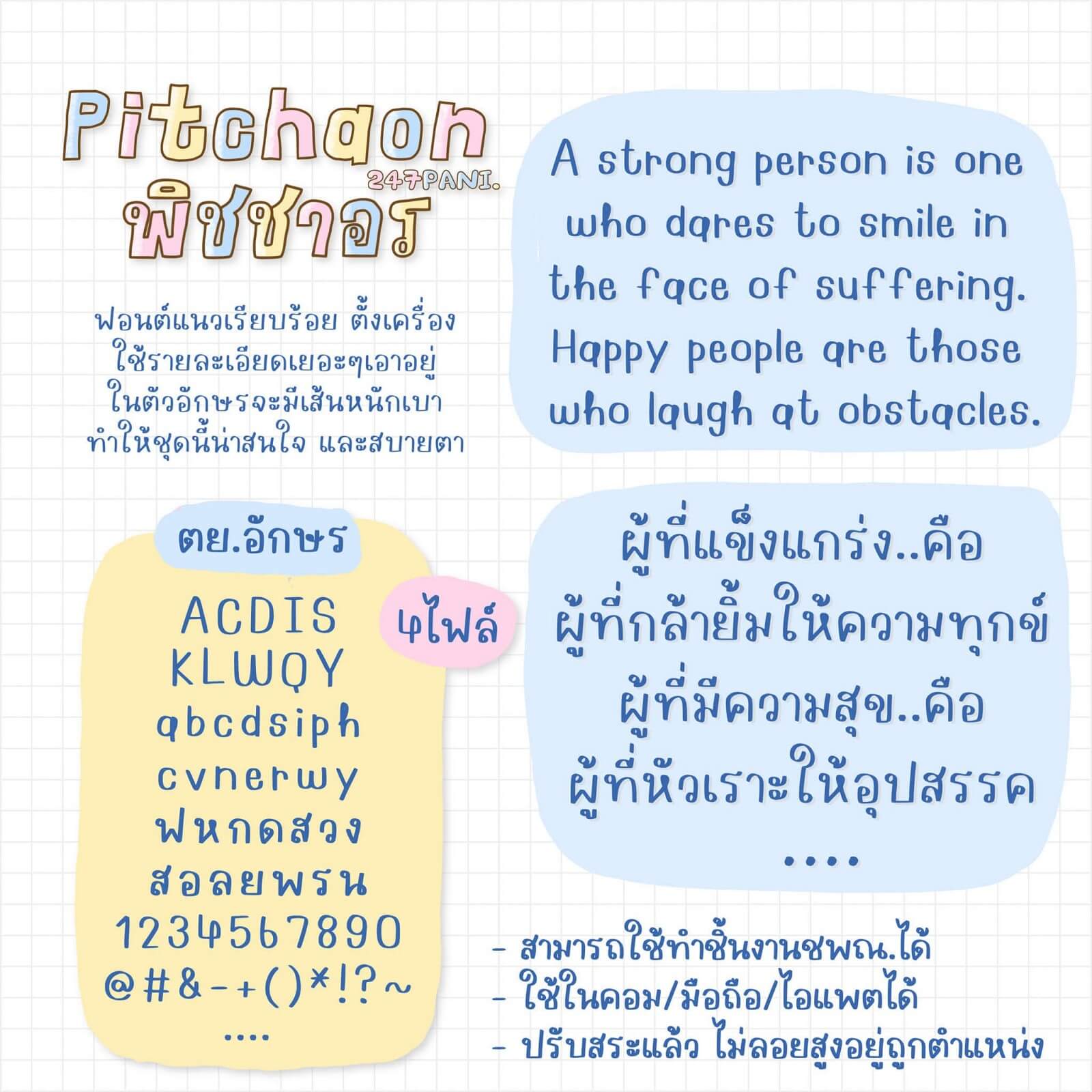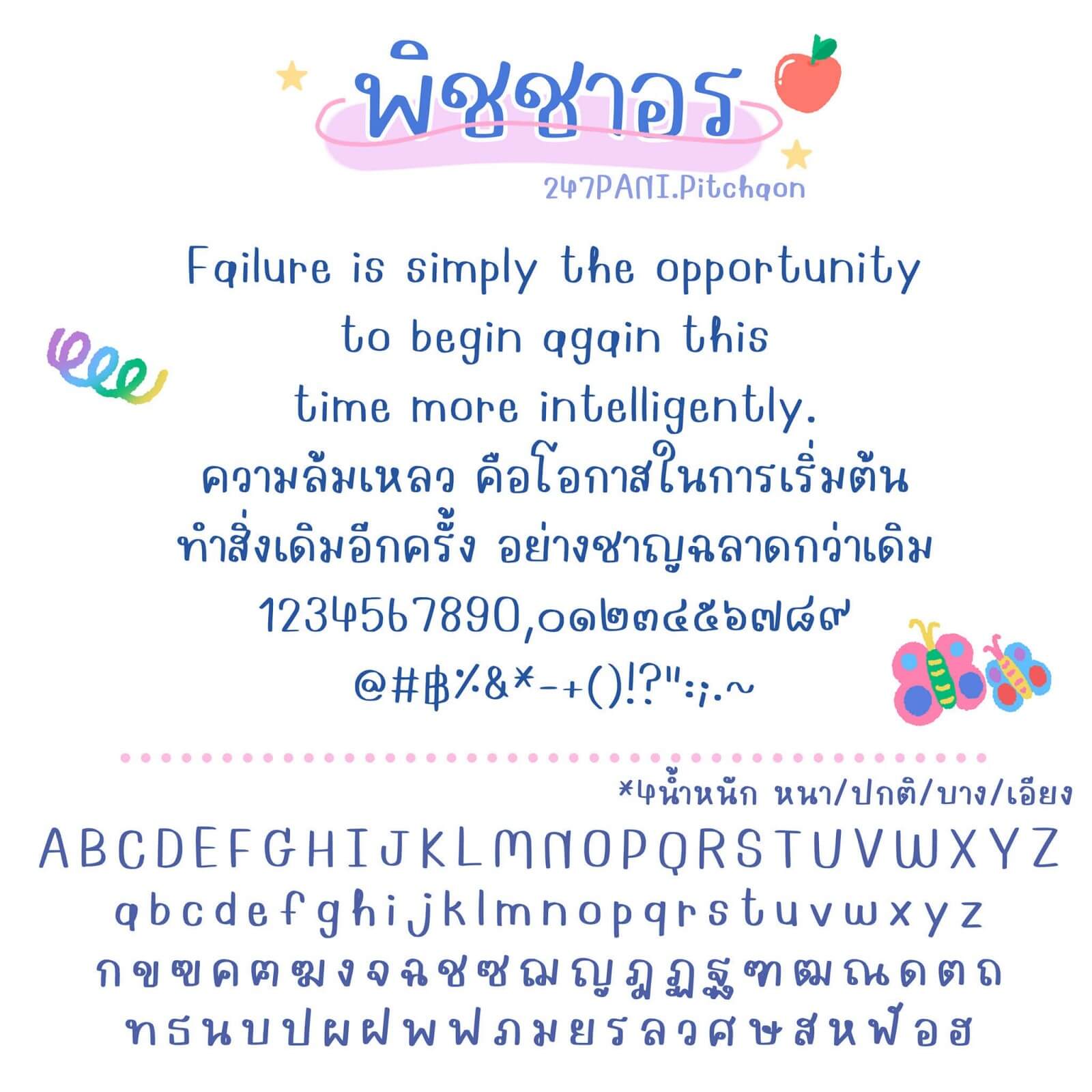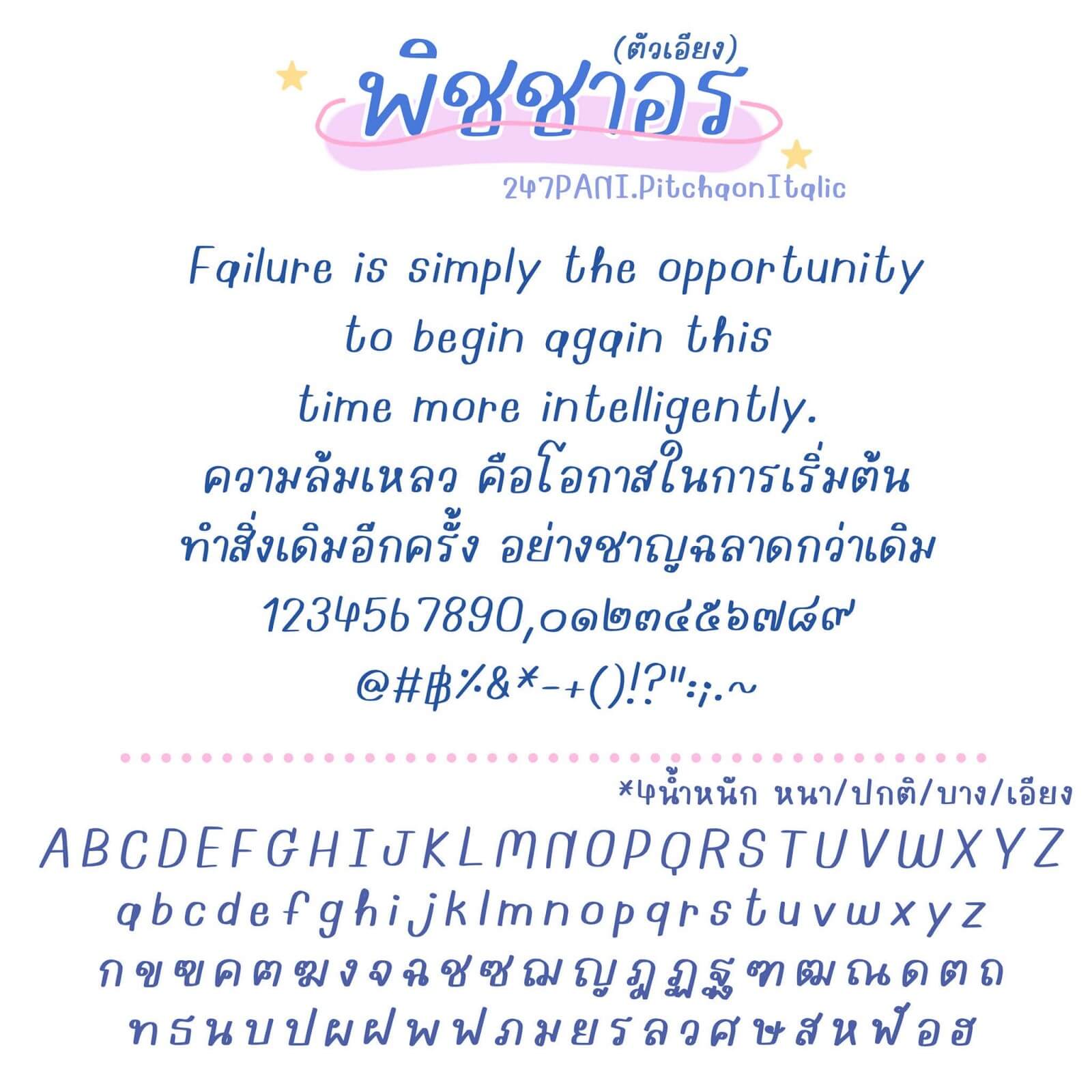
247PANI.พิชชาอร
ฟอนต์ 247PANI.พิชชาอร – ฟอนต์แนวเรียบร้อย ตั้งเป็นฟอนต์เครื่อง จดรายละเอียดเยอะๆ เอาอยู่ ทรงกึ่งทางการ ในตัวอักษรจะมีเส้นหนักเบา ทำให้ชุดนี้ ดูน่าสนใจ และสบายตา
ฟอนต์มี 4 ไฟล์ – น้ำหนัก บาง ปกติ หนา เอียง